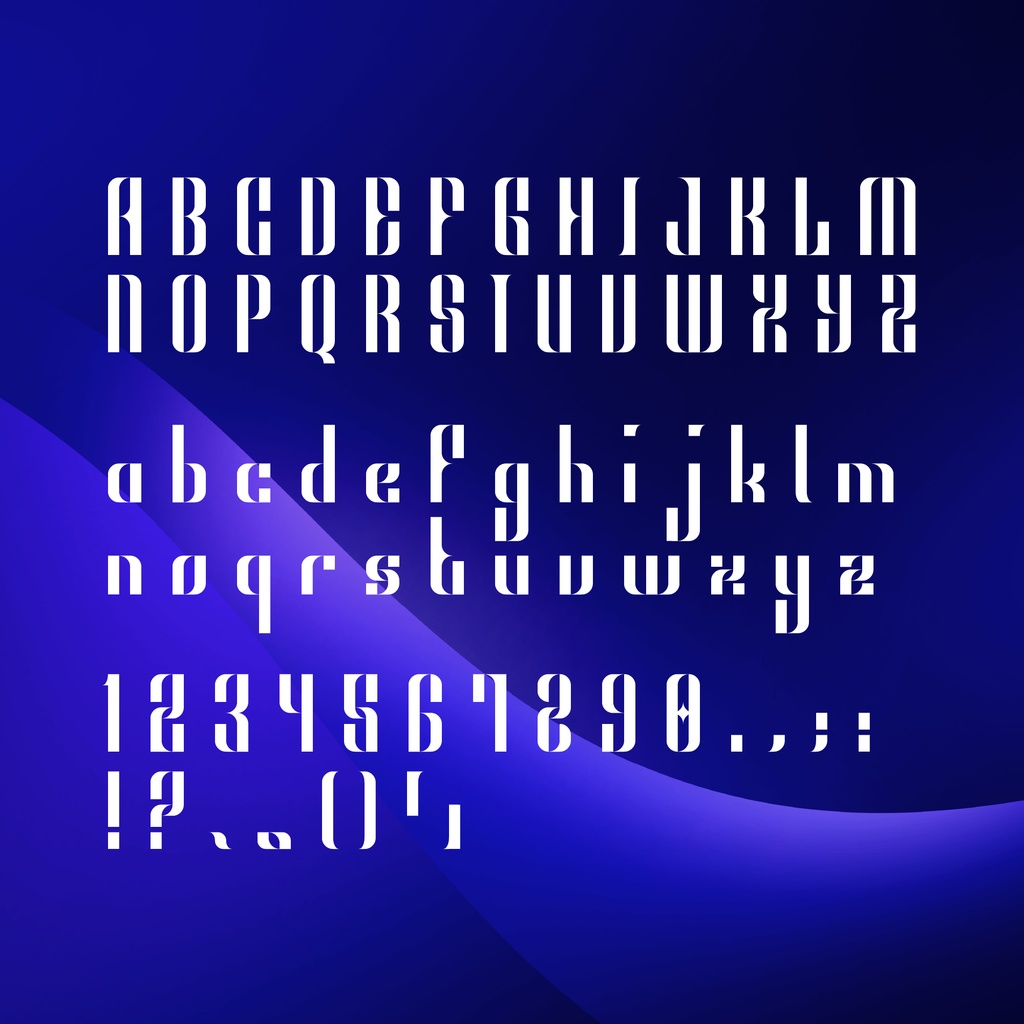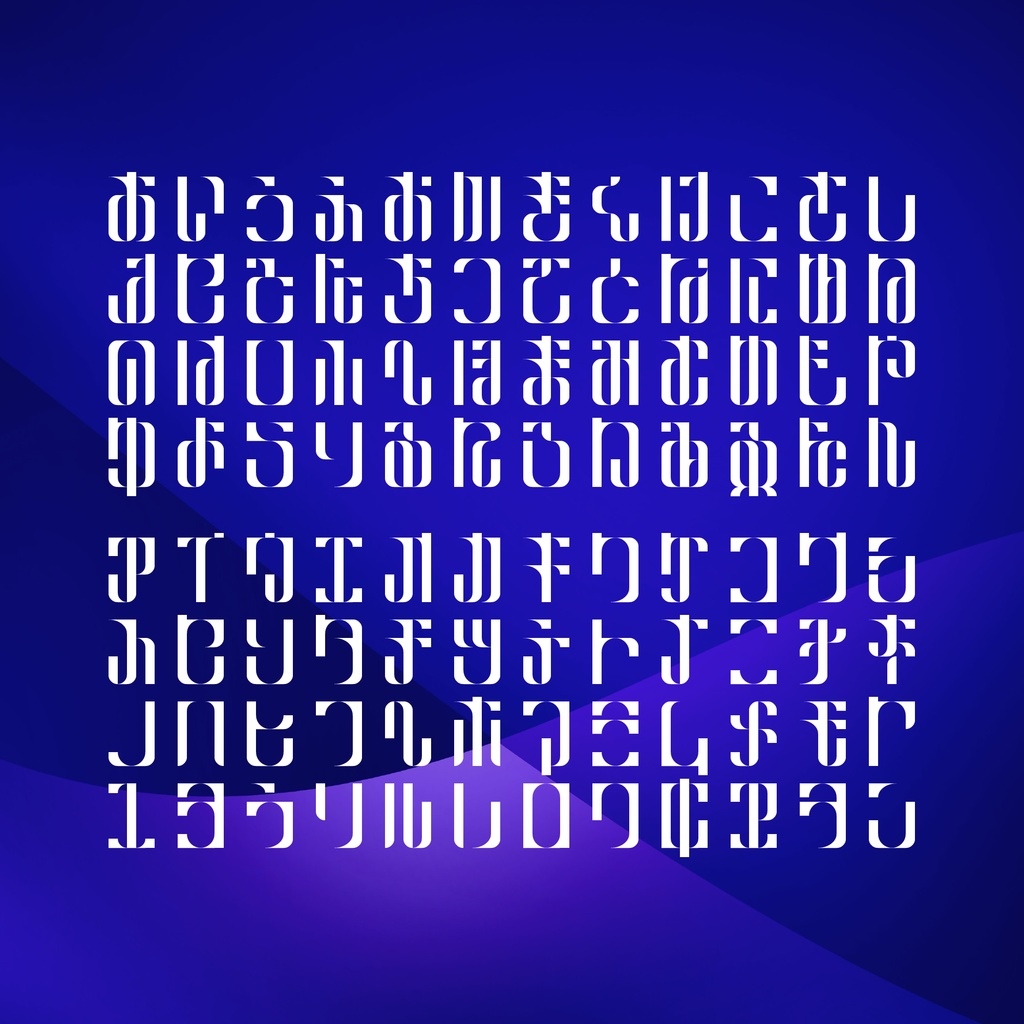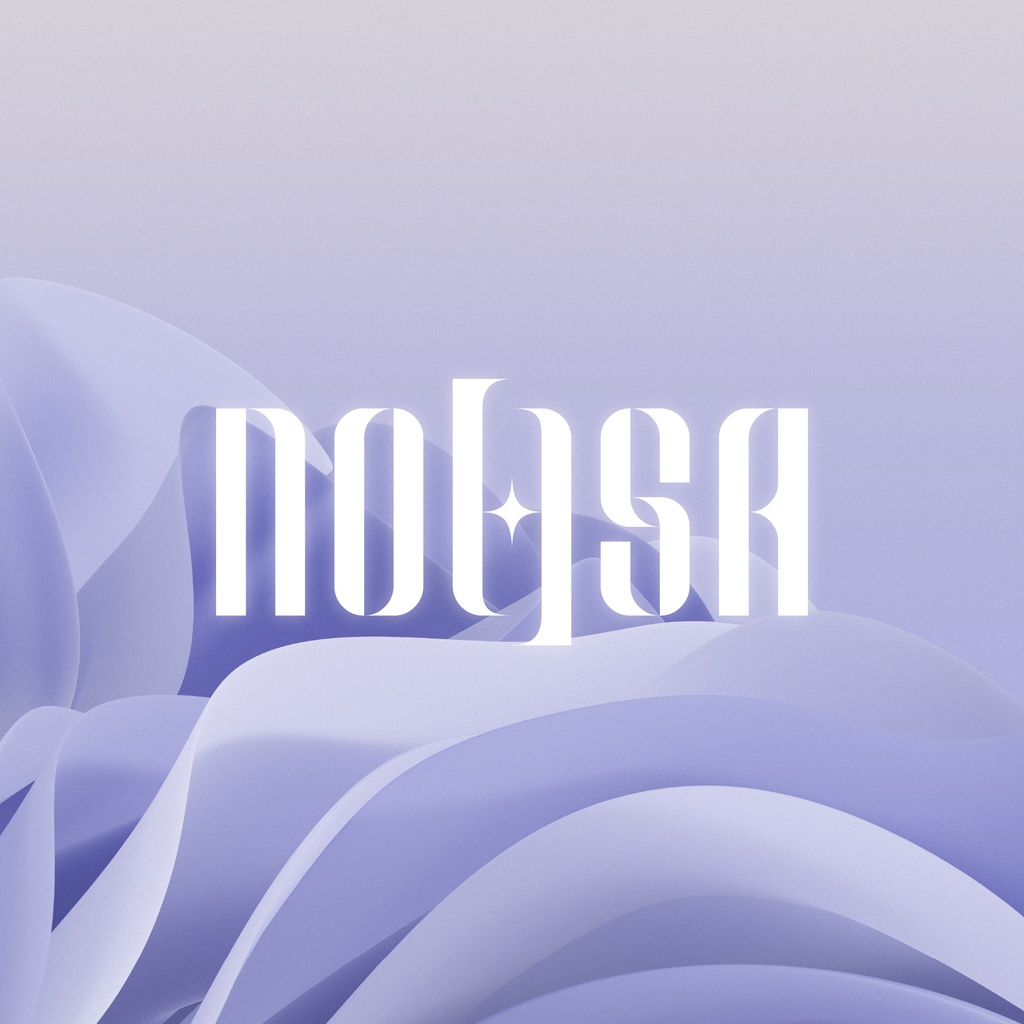
💠 NOSA / の狭 💠 📢📢📢📢📢📢📢📢📢 特記事項 📢📢📢📢📢📢📢📢📢 リツイートで新フォントを配布する企画を開催中。 📢新しいフォントが掲示ツイートが目標達成から1ヶ月間のみ無料配布され、その後は有料となりますが。また、配布開始ツイートが毎回100RTの倍数を超えると、まだ1ヶ月間無料でDLできます。📢 ☕️価格設定には、デザインへの集中力を維持するために、缶コーヒーに大きく依存しているです。 そのため、大体の制作日数×日本での缶コーヒーの値段でフォントの価格を算出することにします。☕️ 📢📢📢📢📢📢📢📢📢 デザイン説明 📢📢📢📢📢📢📢📢📢 日本語のゴシックフォントには、あまりゴシック風英語フォントの超目立つの特徴がないことに気づきました。そのため、このフォントて、日本語の仮名がゴシック風の超目立つの特徴に適合するかどうかを試してみました。 未来風の機械的な反復や均一な無感情と、ゴシック風英語フォントの鋭い角と丸みの優雅さが融合された幅可変フォントです。 📢📢📢📢📢📢📢📢📢 利用規約 📢📢📢📢📢📢📢📢📢 個人、商用どちらでも利用可能です。 ✨フォントが使用されたら、ツイッターにお知らせくださいhttps://twitter.com/amari_design✨ 本素材を使用した作品については、リツイートなどの形で宣伝させていただく場合があります。 フォントのインストール等の技術的なサポートはいたしません。使用して発生したと思われる如何なる問題についても、作者は責任を負わないものとします。 著作権を放棄することはありません。 商標を登録したり、作者であると主張したり、データ自体を販売または再販したりすることは禁じられています。 このコンテンツの最終的な解釈権は作者に帰属します。 内容補充とバージョン更新は製作続けるです。使用する際は最新バージョンにご注意ください。 📢📢📢📢📢📢📢📢📢 収録內容 📢📢📢📢📢📢📢📢📢 ラテン文字、数字、仮名だけてを含む276グリフが含まれています。 ーーーーーーーーーーーー Twitter:https://twitter.com/amari_design Behance:https://www.behance.net/9f45706b ーーーーーーーーーーーー